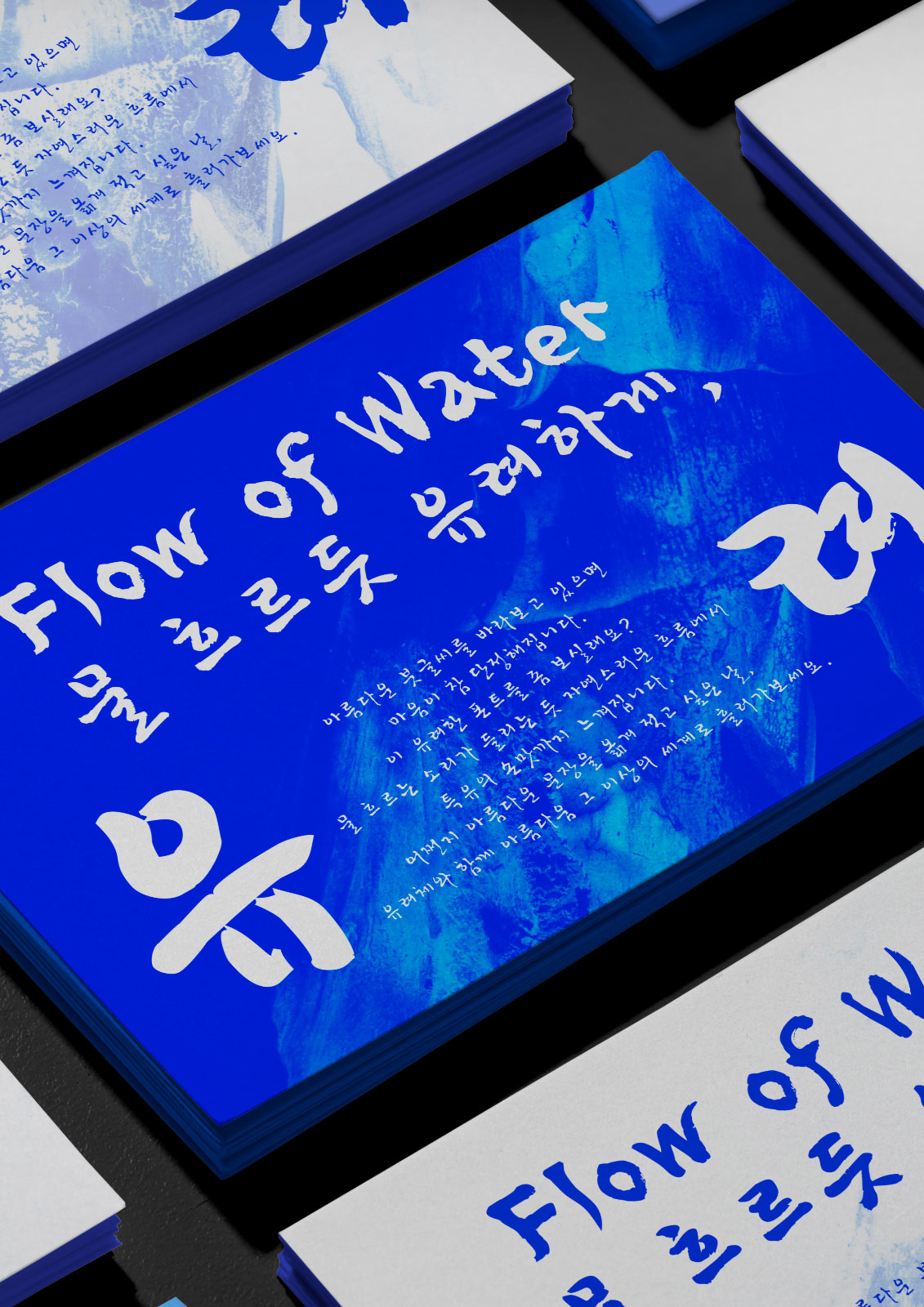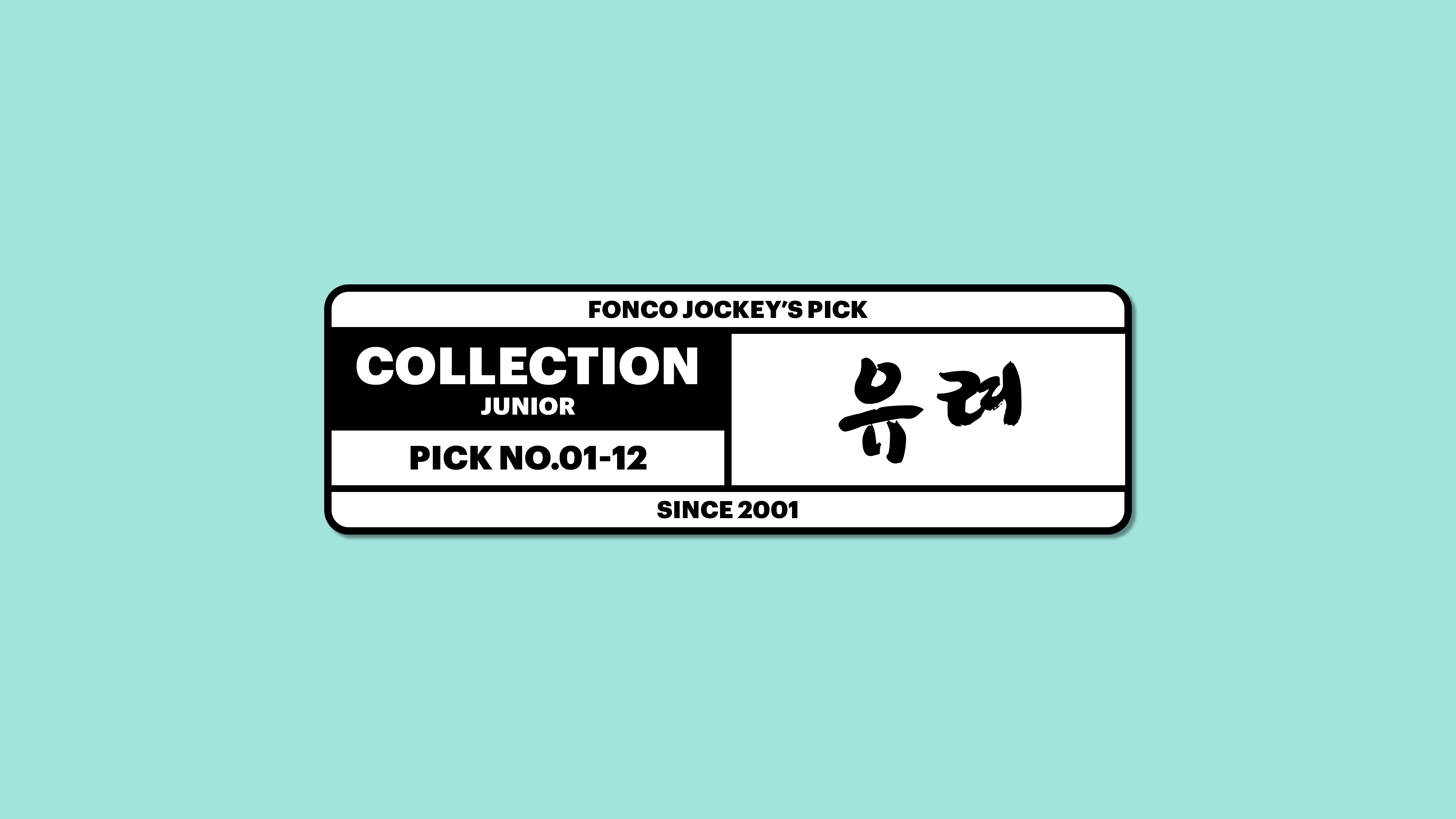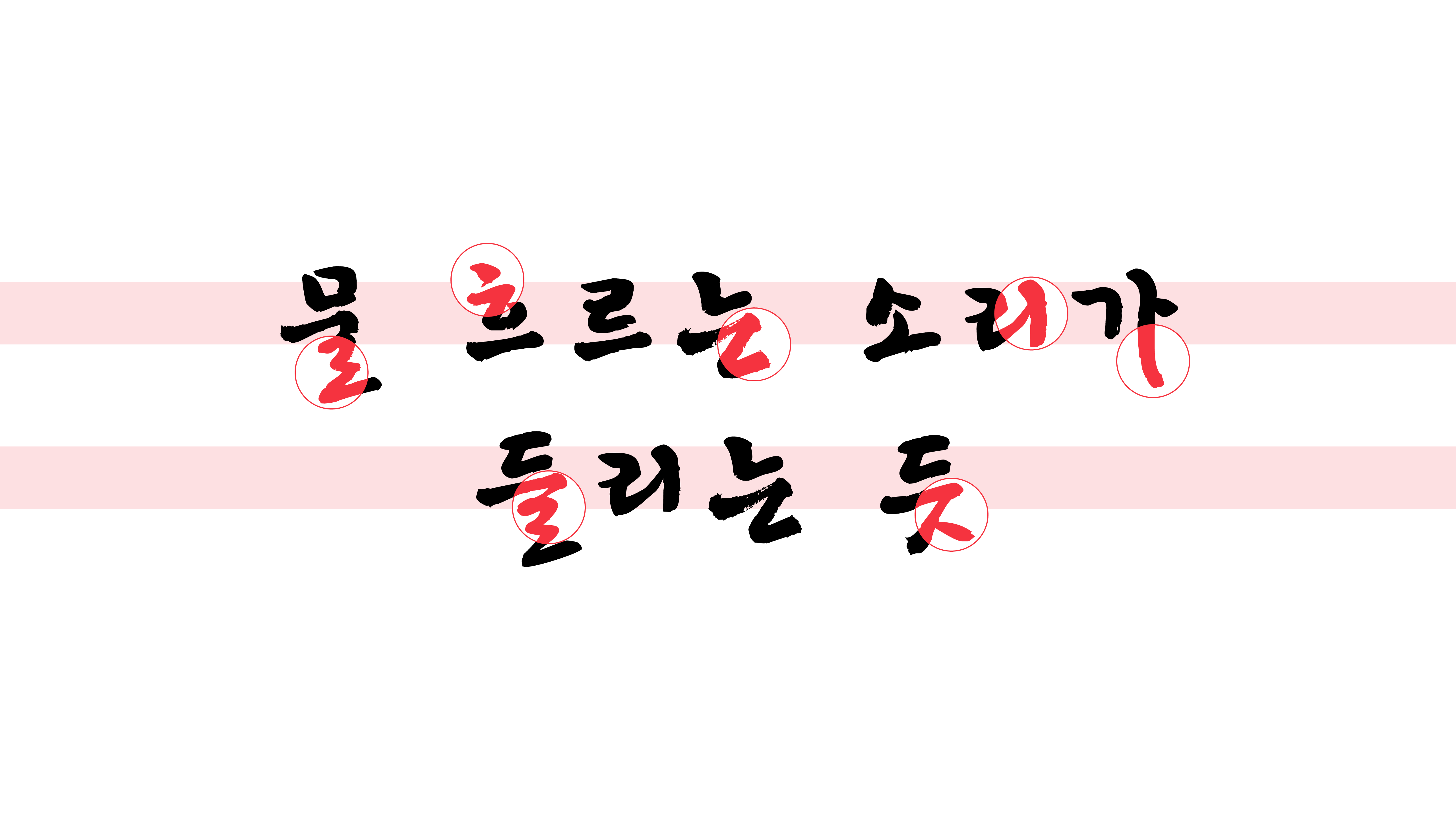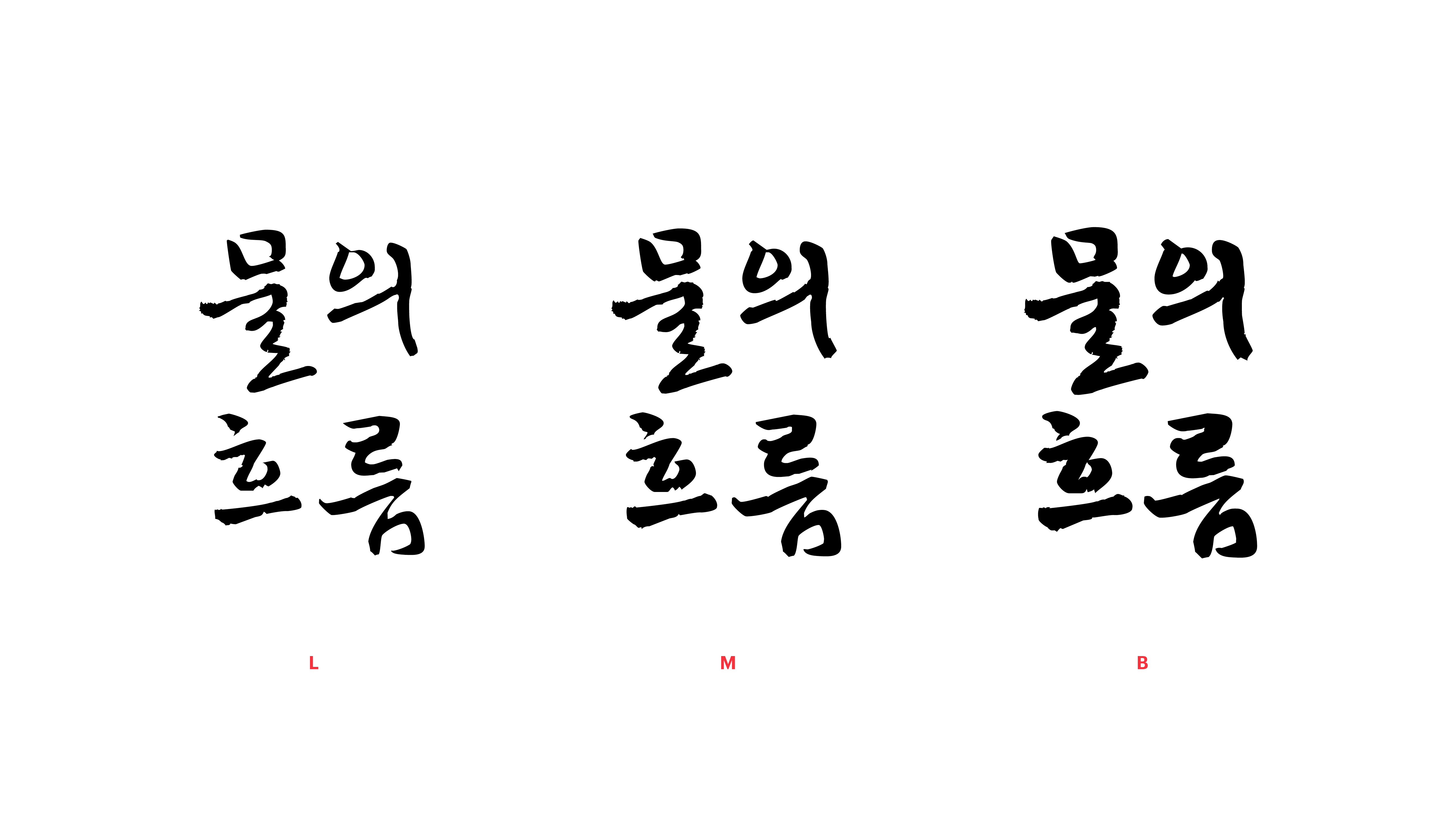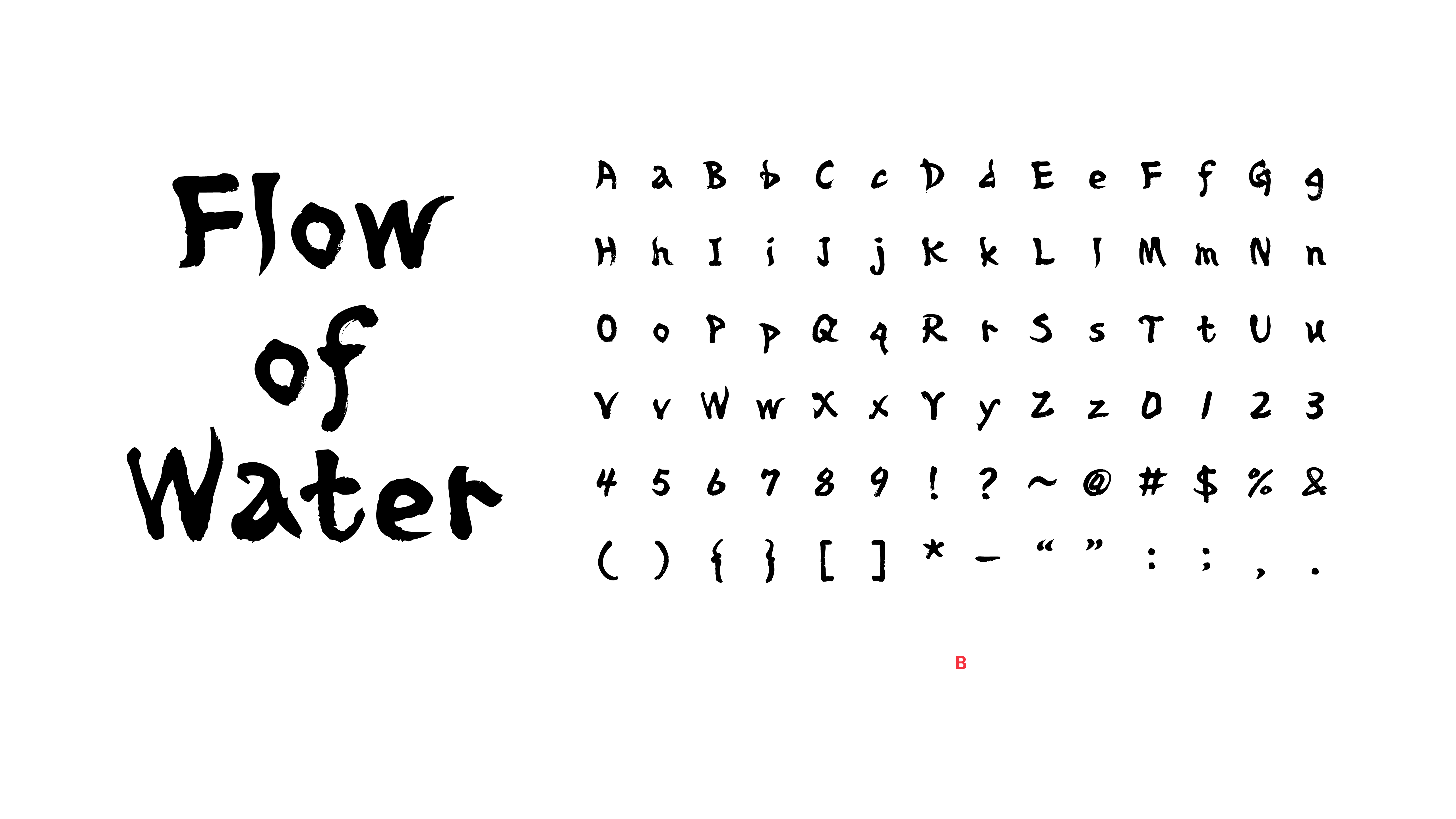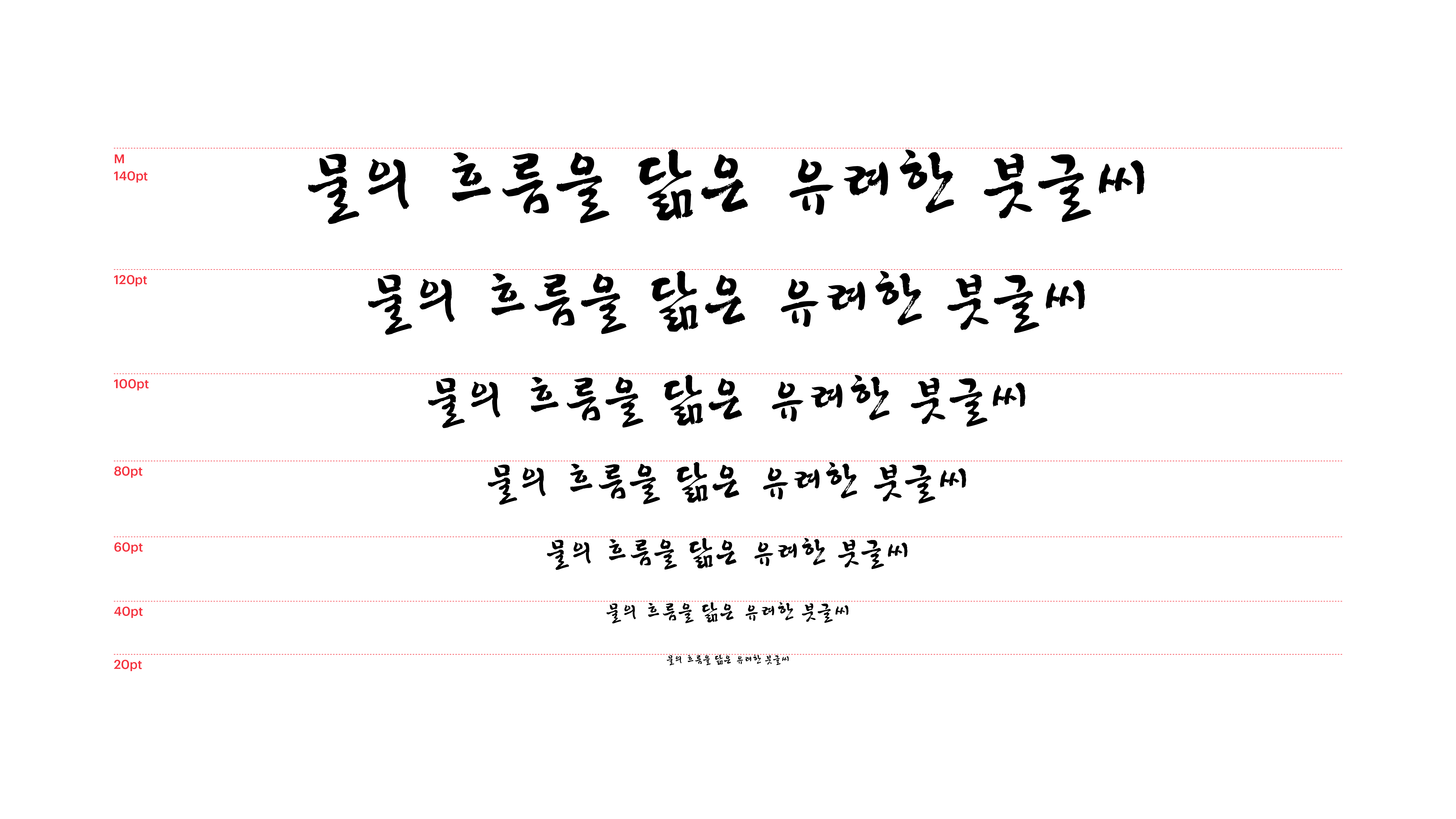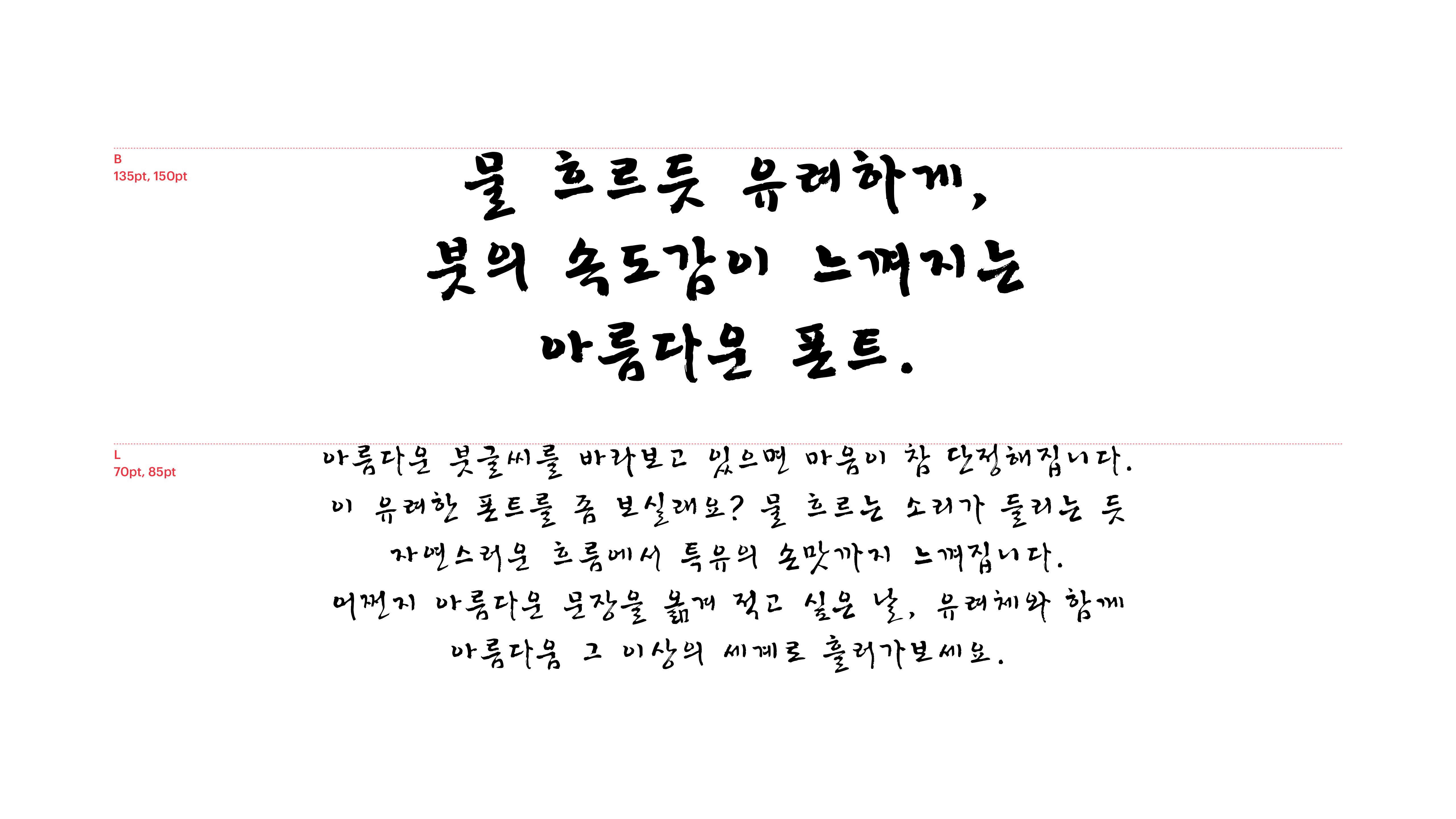
유려
Yoon 유려
아름다운 붓글씨를 바라보고 있으면 마음이 참 단정해집니다. 이 유려한 폰트를 좀 보실래요? 물 흐르는 소리가 들리는 듯 자연스러운 흐름에서 특유의 손맛까지 느껴집니다. 어쩐지 아름다운 문장을 옮겨 적고 싶은 날, 유려체와 함께 아름다움 그 이상의 세계로 흘러가보세요.